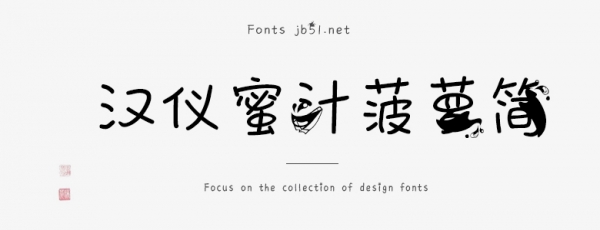
漢儀蜜汁菠蘿簡(jiǎn)是由漢儀字庫(kù)出品,字體筆觸適中,字形圓潤(rùn),具有很好的視覺(jué)感,適合應(yīng)用于藝術(shù)設(shè)計(jì)、平面宣傳設(shè)計(jì)、網(wǎng)頁(yè)設(shè)計(jì),書法字帖等領(lǐng)域,需要的朋友可以前來(lái)本站下載。